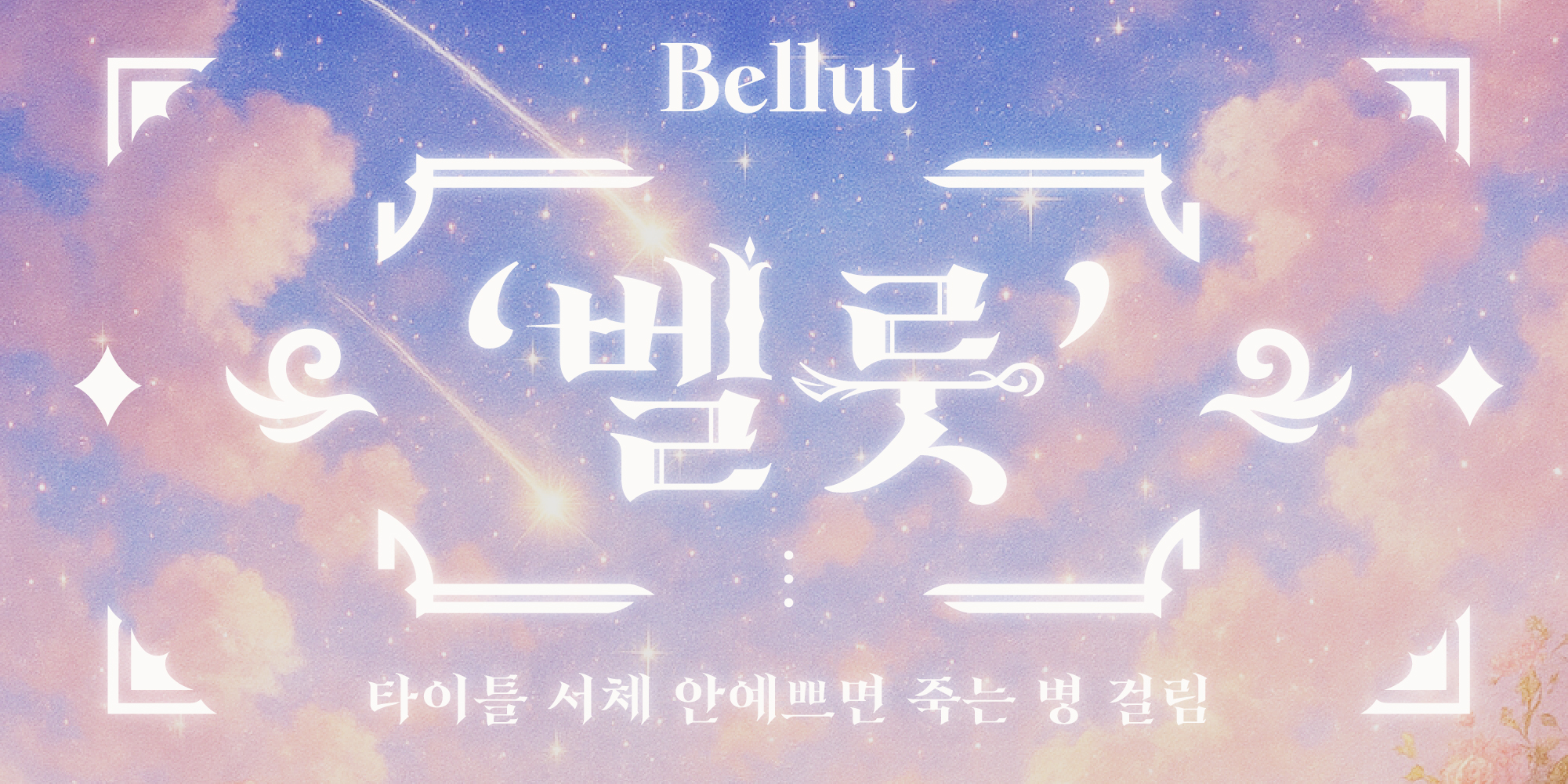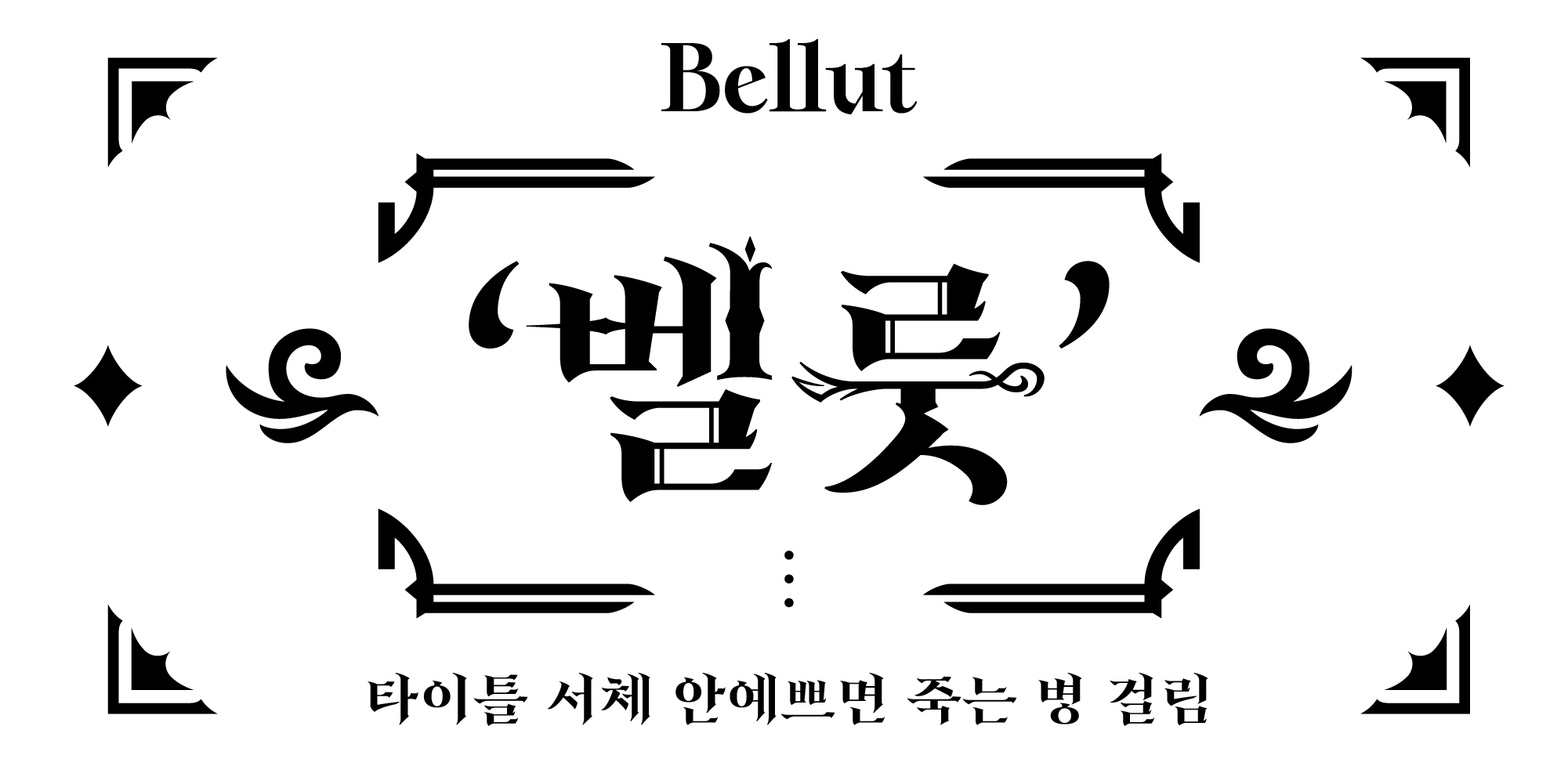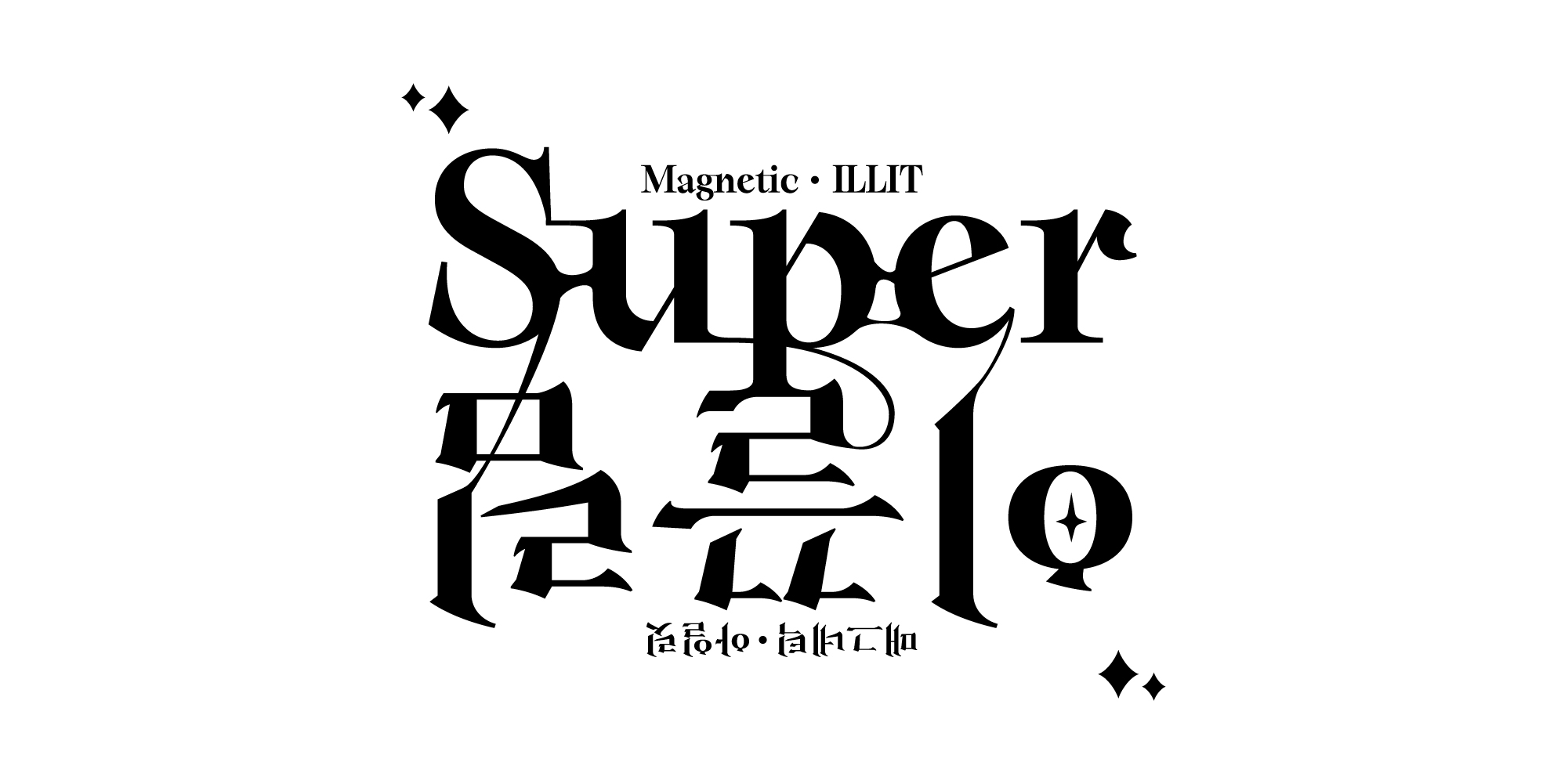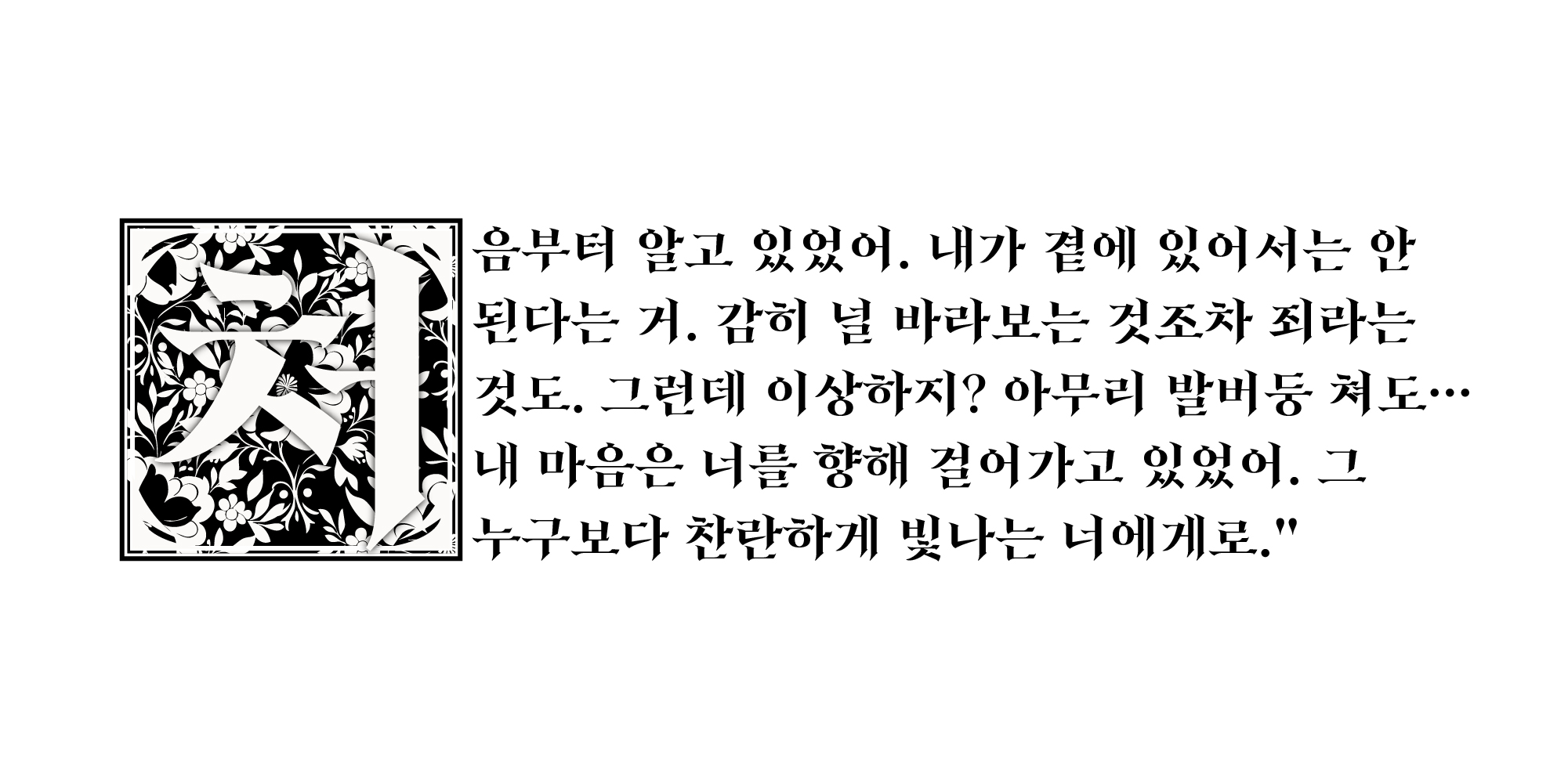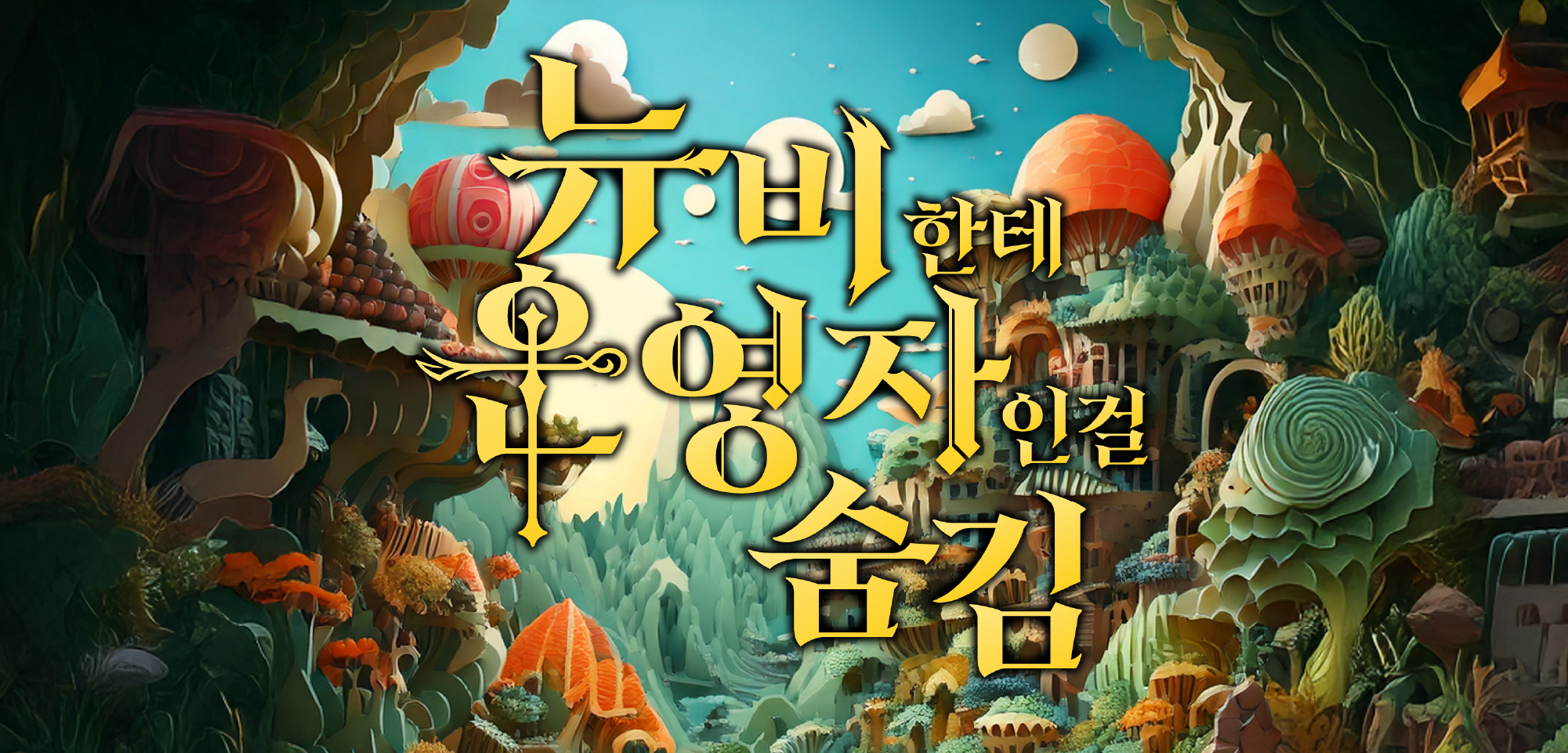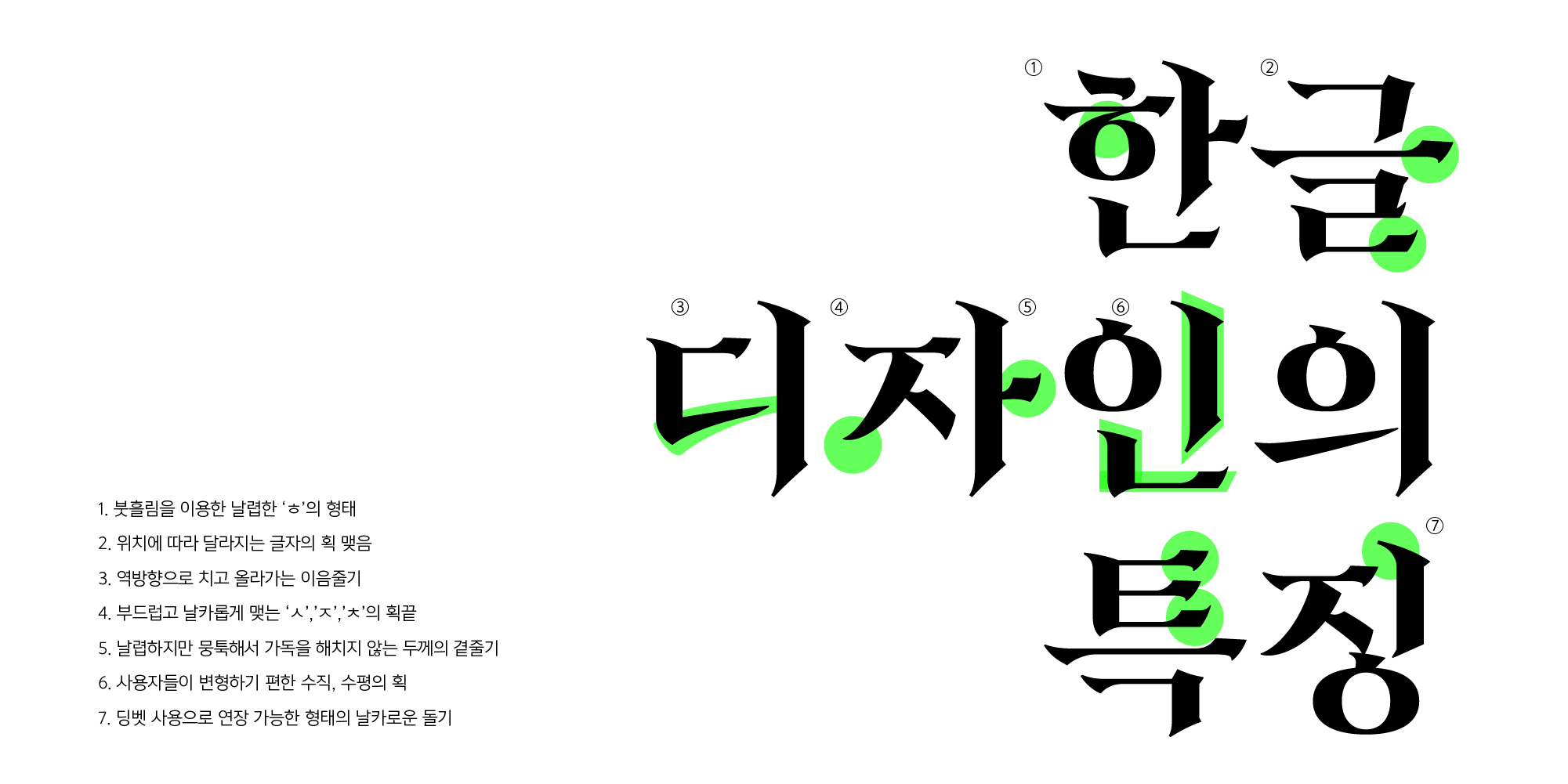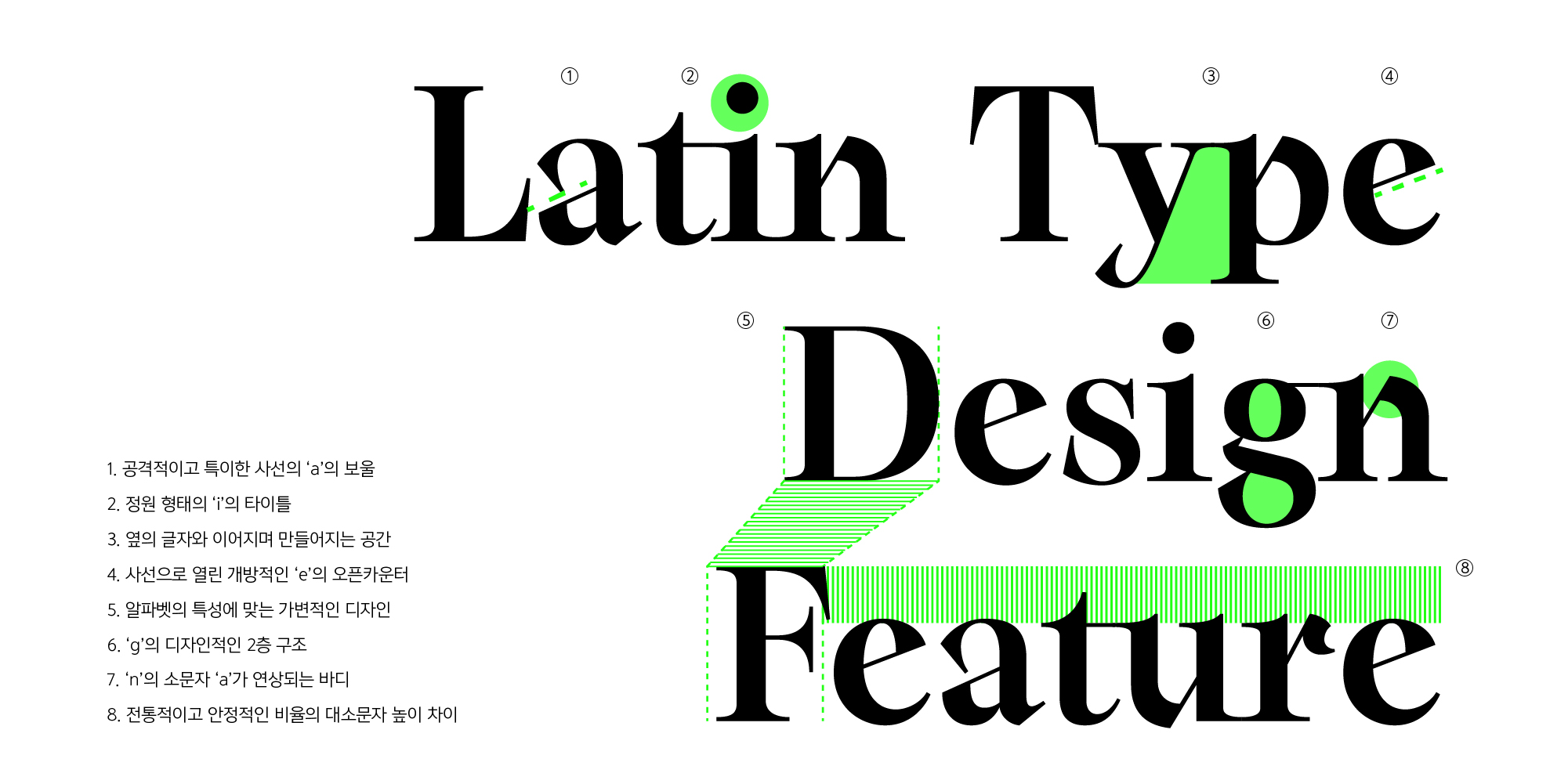
감정을 담은 곡선과, 구조적인 인상을 주는 조형이 공존하는 타이틀 전용 폰트로, 시각적 임팩트와 감성적인 뉘앙스를 동시에 전달할 수 있도록 설계되었습니다. 또한 딩벳 요소와 교체 가능한 한글 모음 등, 타이틀 디자인을 보다 쉽고 빠르게 완성할 수 있는 도구로 구성되어 있습니다.
5am 벨룻